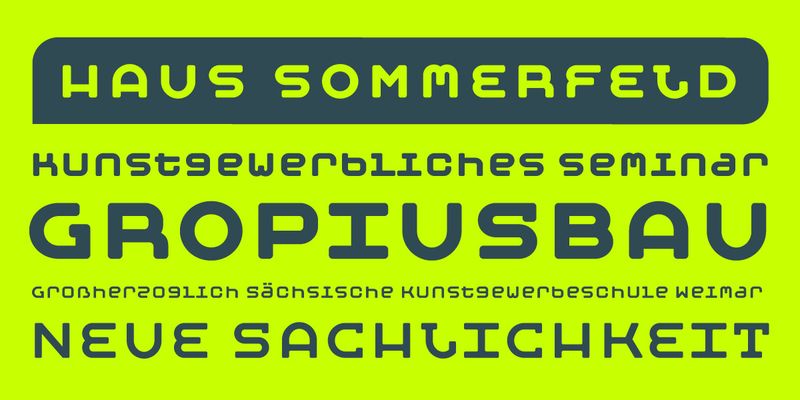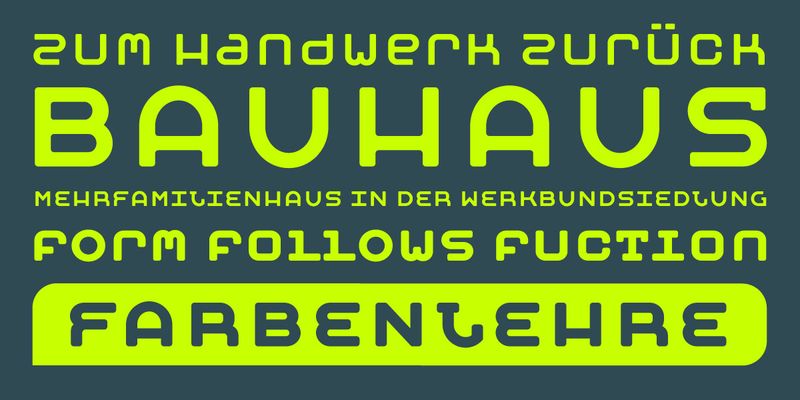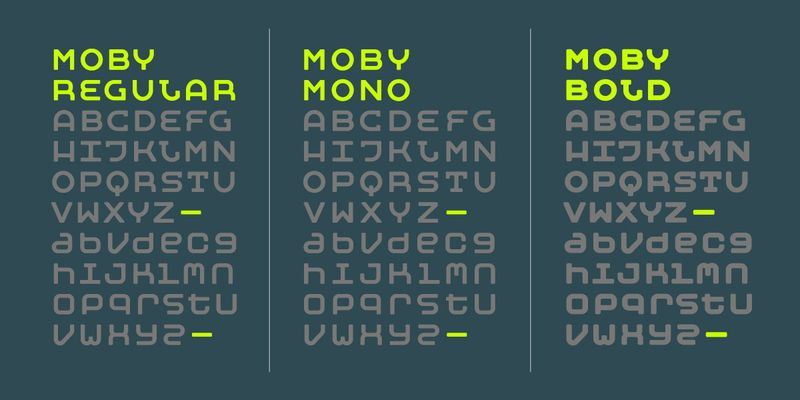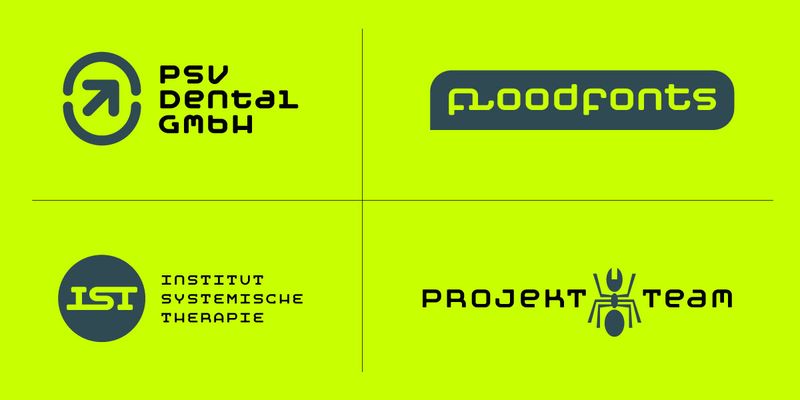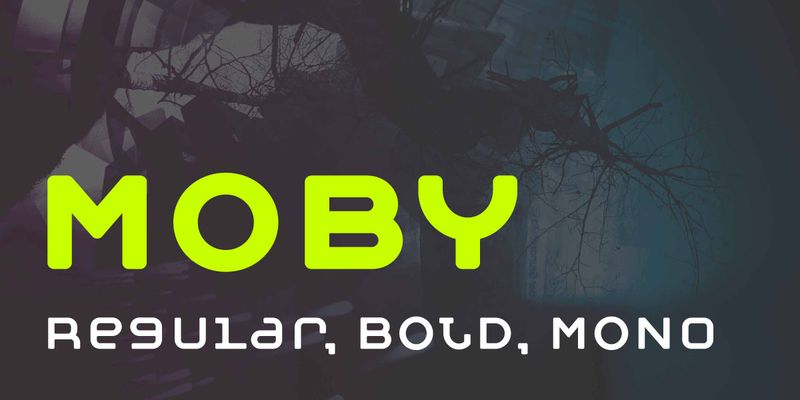
Moby a été créée en 2002 par Felix Braden en tant que police d’entreprise et de titre pour le bureau de design Glashaus, basé à Cologne. Les formes de lettres sont inspirées du logotype de la légendaire école Bauhaus de Weimar (Allemagne) et sont créées sur une grille de 5 x 5 pixels. La famille est livrée avec 3 polices : Moby Bold, Regular et Monospaced.